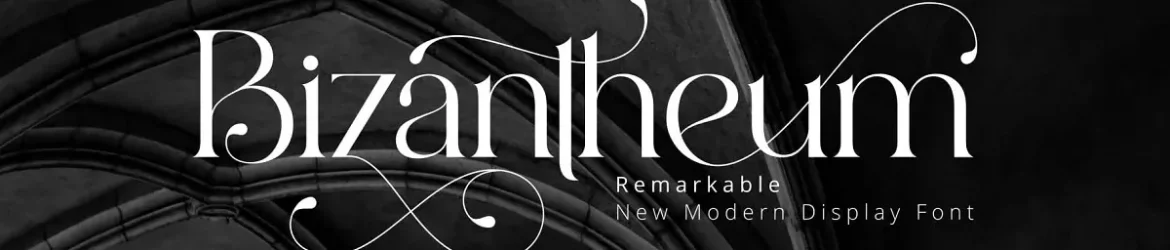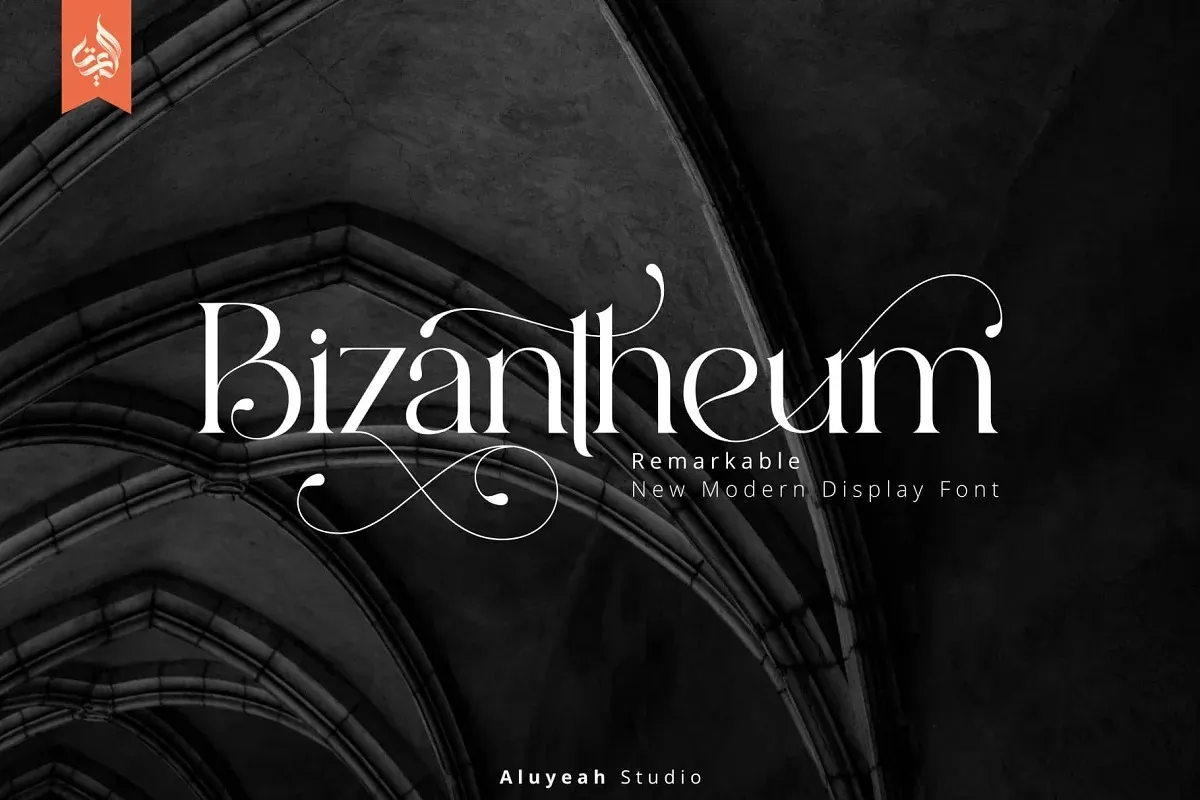
Bizantheum Font – Fonte Grátis
Bizantheum Font
A Bizantheum Font é uma elegante escolha para aqueles buscando um equilíbrio entre modernidade e nostalgia. Inspirada nos majestosos edifícios bizantinos do passado, ela oferece tanto a modernidade quanto o encanto nostálgico. Perfeita para aplicações variadas como logotipos, revistas e mídias sociais digitais, esta fonte é um sucesso em todas essas áreas. Com 130+ alternativas estilosas e fáceis de usar, ela garante que seu design seja único e atraente sem grandes esforços. Seu design inspirado na majestosidade dos edifícios bizantinos do passado é uma delícia para os olhos. Essa fonte não só oferece uma sensação nostálgica de outrora, mas também traz um toque moderno que combina perfeitamente com qualquer estilo de design. O fato de estar disponível em 130+ alternativas superficialmente estilosas e fáceis de usar é o único obstáculo para você explorar todas as possibilidades criativas da Bizantheum Font, garantindo que seu trabalho seja imediatamente reconhecível.